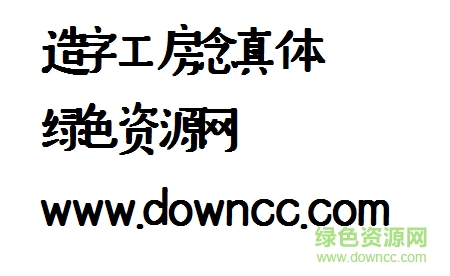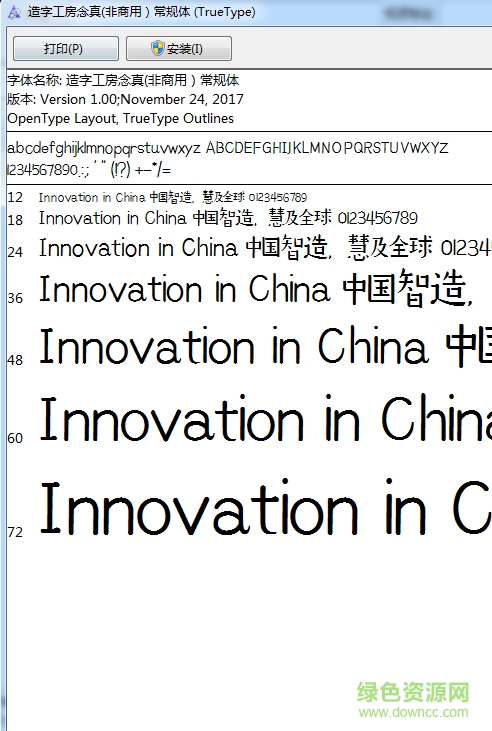
造字工房念真體樸素?zé)o華,飽含古時之風(fēng)韻,能帶給人們一種懷舊感覺,這種個性的字體適用于傳統(tǒng)產(chǎn)品,民間藝術(shù)品等主題。
造字工房創(chuàng)立于二零零九年年初,專注于漢字新字體字形設(shè)計與開發(fā)。整個設(shè)計團隊由從事多年商業(yè)設(shè)計的平面設(shè)計師和專業(yè)字體設(shè)計師組成,我們對漢字持有深厚的感情,多年來一直致力于漢字字體字形的設(shè)計、應(yīng)用和研究。